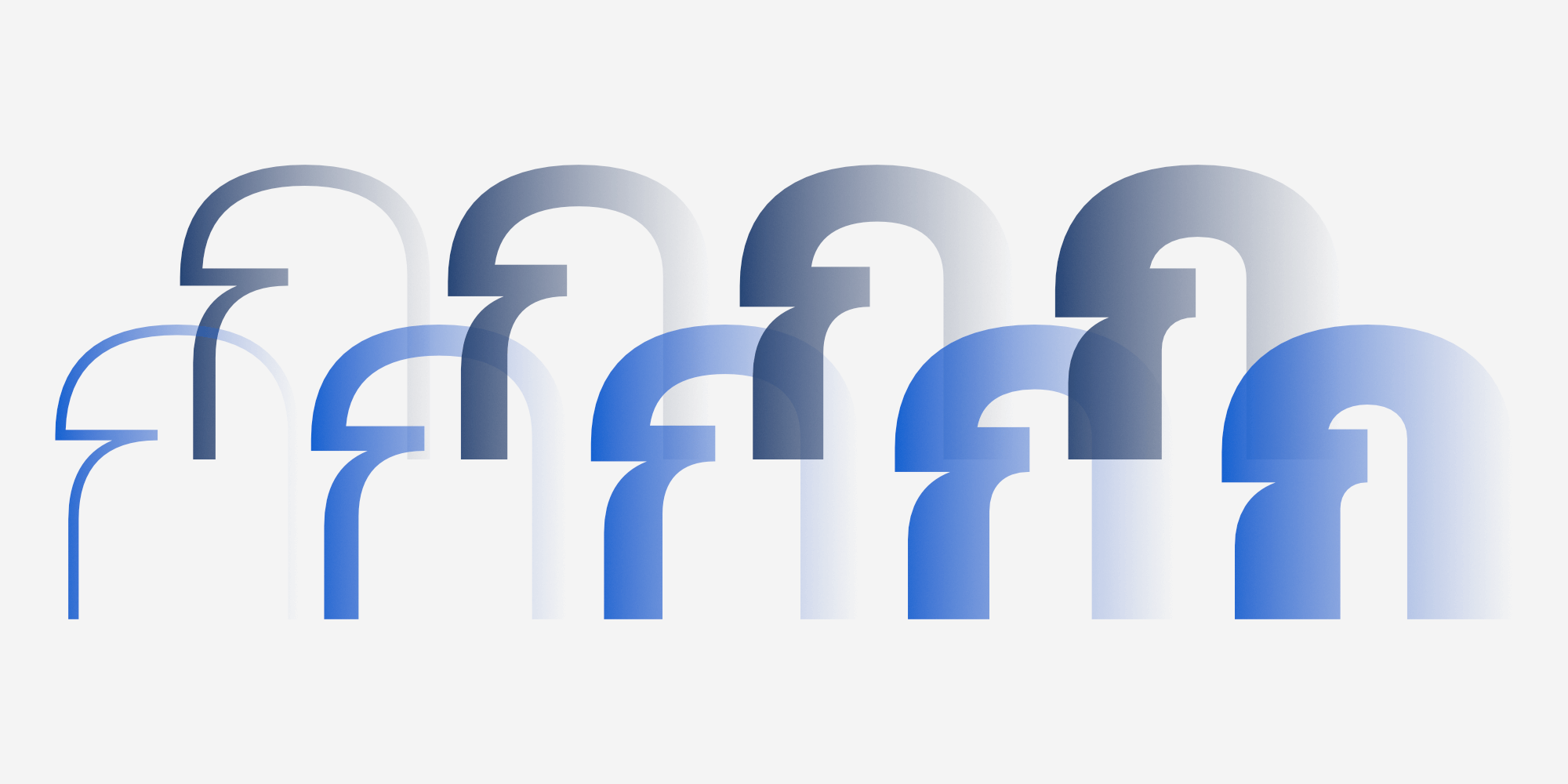
Mahasal เป็นแบบอักษรแซนเซอริฟที่เน้นความเรียบง่าย มีหลายความกว้างตั้งแต่แคบสุดไปจนถึงกว้างสุด และมีหลายน้ำหนักตั้งแต่บางสุดไปจนถึงหนาสุดของแต่ละความกว้าง รวมแล้วมีให้เลือกใช้ถึง 162 รูปแบบ
โดยที่ความกว้างแคบมีโครงสร้างตัวอักษรเป็นแบบ Capsulated จากนั้นความกว้างปกติจนถึงกว้างสุดเป็นโครงสร้าง Geomatric การขยายความกว้างยึดตามมาตรฐาน OS/2.usWidthClass specification
โดยที่ความกว้างปกติคือ 100% ความกว้างแคบสุดคือ 50% ความกว้างกว้างสุดคือ 200% เมื่อมาเทียบกับฟอนต์ Anantason Reno และ Prachason Neue แล้วนั้นฟอนต์ Mahasal จึงมีความกว้างและความแคบมากกว่าหลายเท่าตัว ดังนั้นฟอนต์ Mahasal เป็นอีกหนึงฟอนต์อเนกประสงค์ที่สามารถใช้ในสื่อประชาสัมพันธ์ได้หลากหลายประเภทหลากหลายความกว้าง